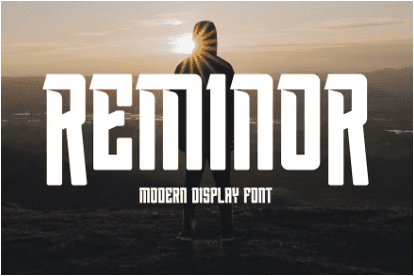
Reminor Font
Представляем наш новый продукт Reminor Font - Современный шрифт
Шрифт Reminor — Modern Font — это смелый и аутентичный дисплейный шрифт. Шрифт подходит для всех брендинговых проектов, таких как логотип, печать на футболках, киберспорт и т. д. исключительный в широком диапазоне контекстов.